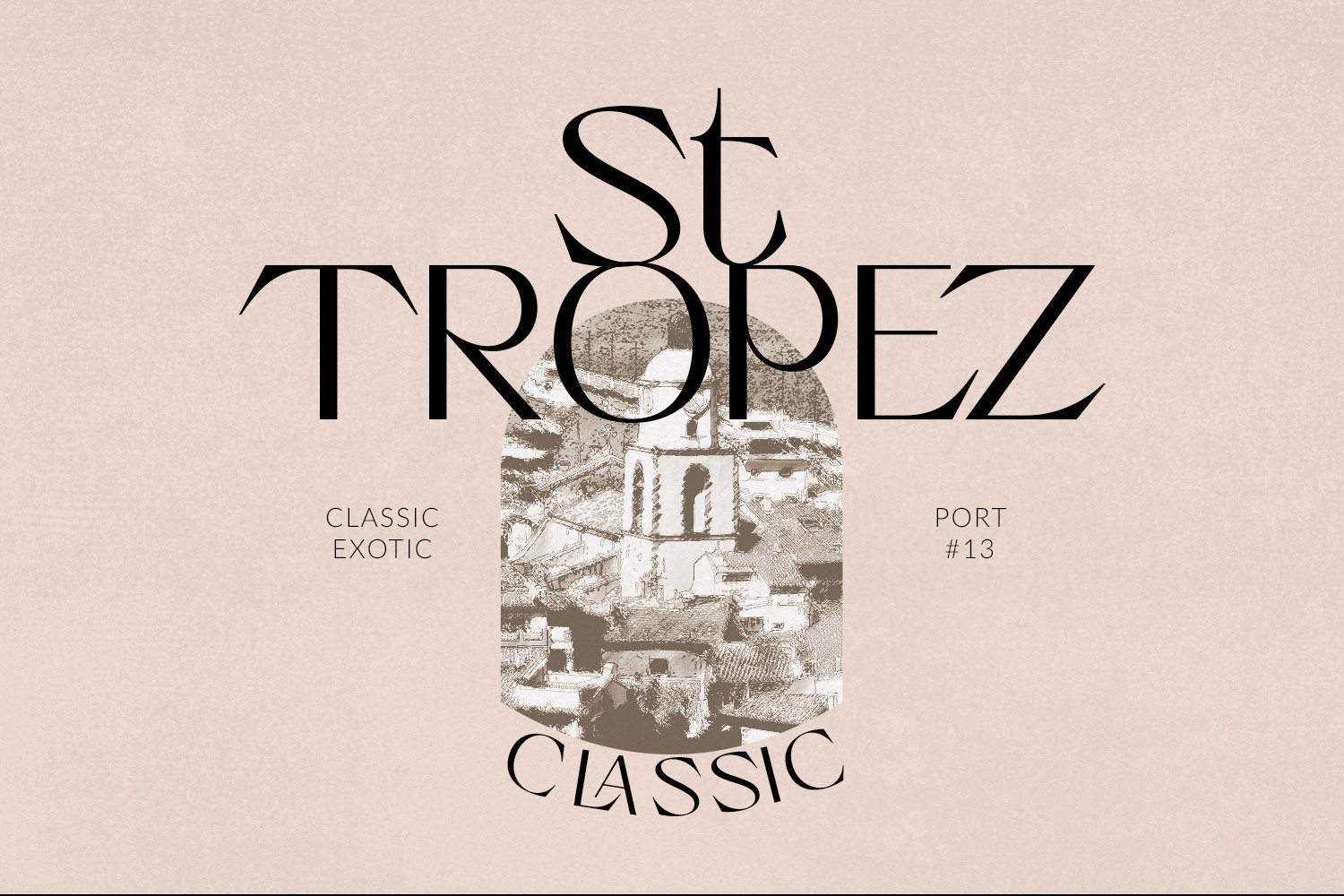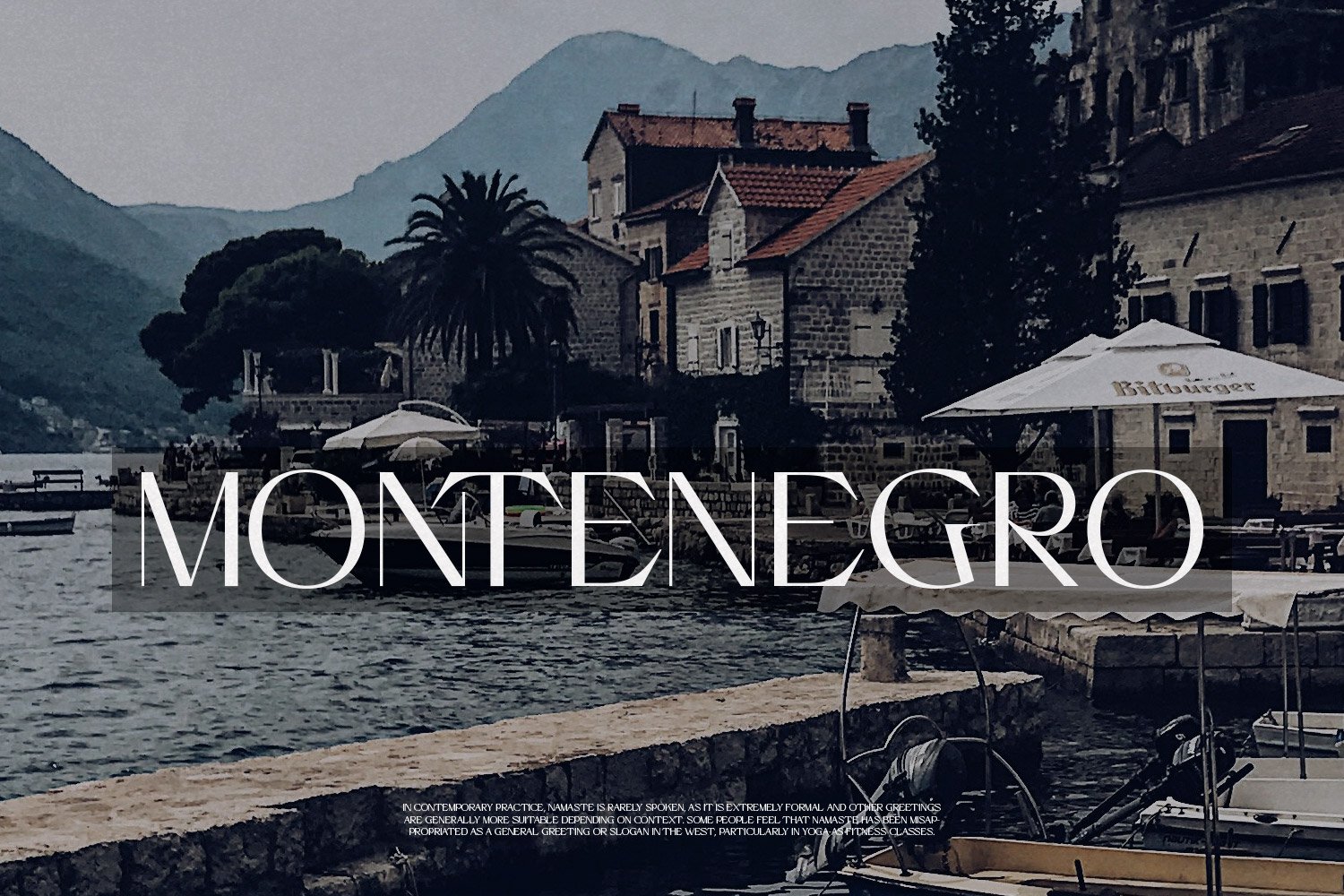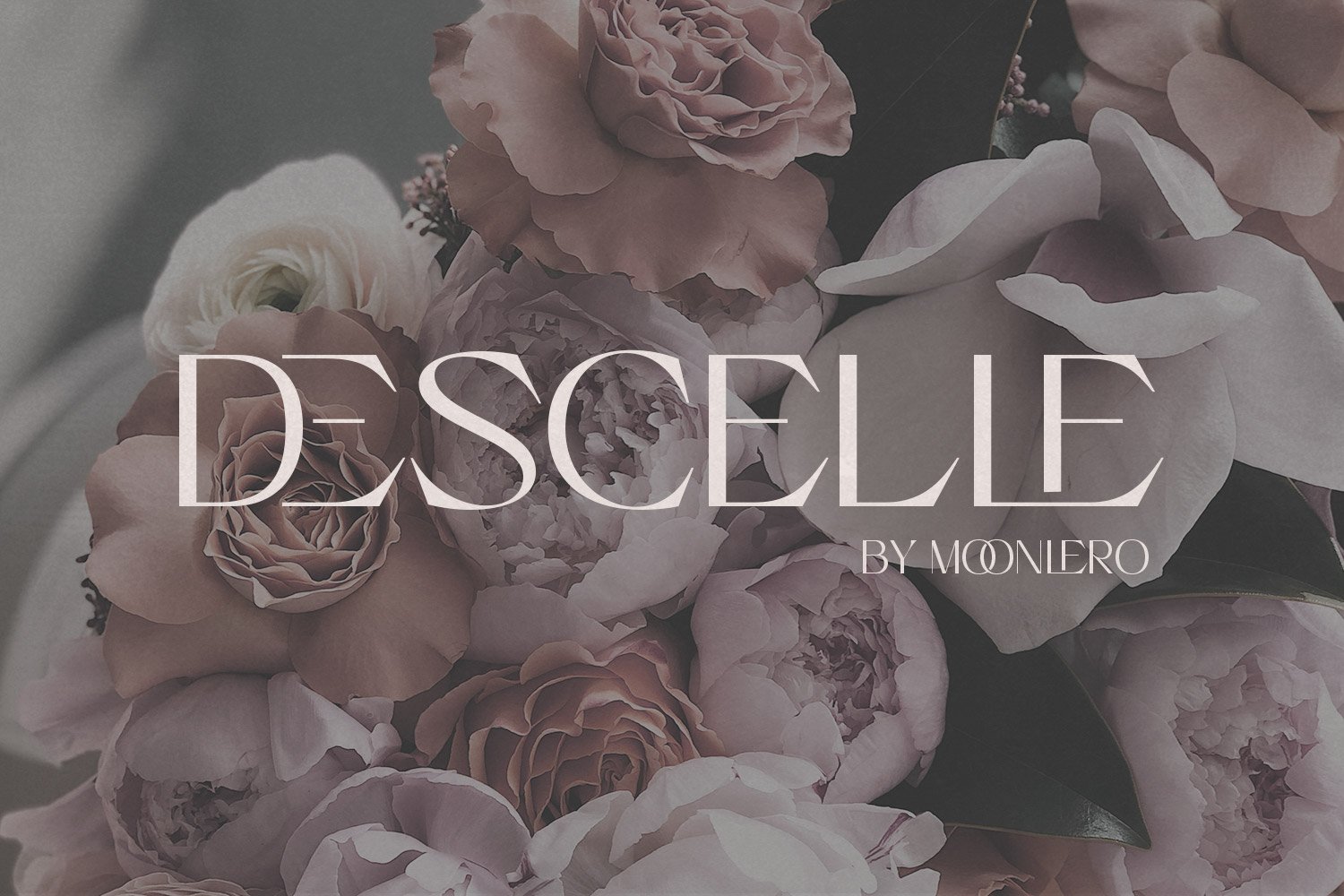
Greyst - Exotic Modern font, với một thiết kế hiển thị đơn giản và độc đáo với hàng chục chữ ghép. Font chữ đa năng này phù hợp nhất cho việc xây dựng thương hiệu, dự án thiết kế web, biểu tượng và hơn thế nữa với hỗ trợ đa ngôn ngữ, số và ký hiệu tiền tệ.